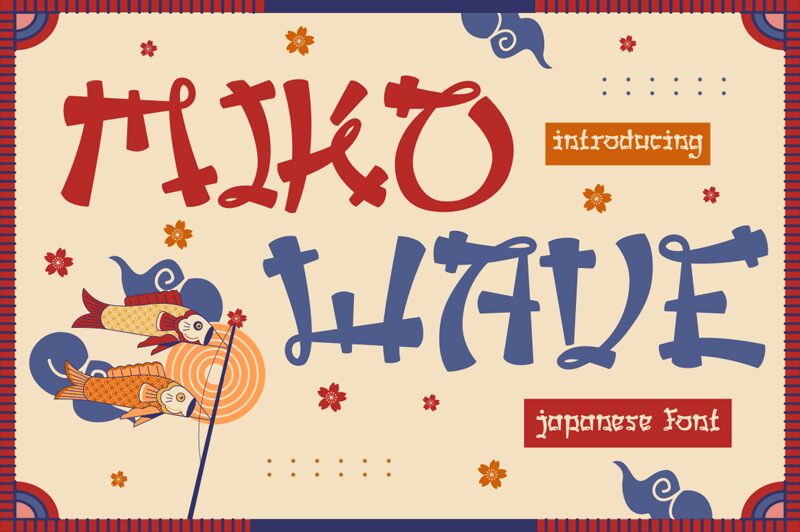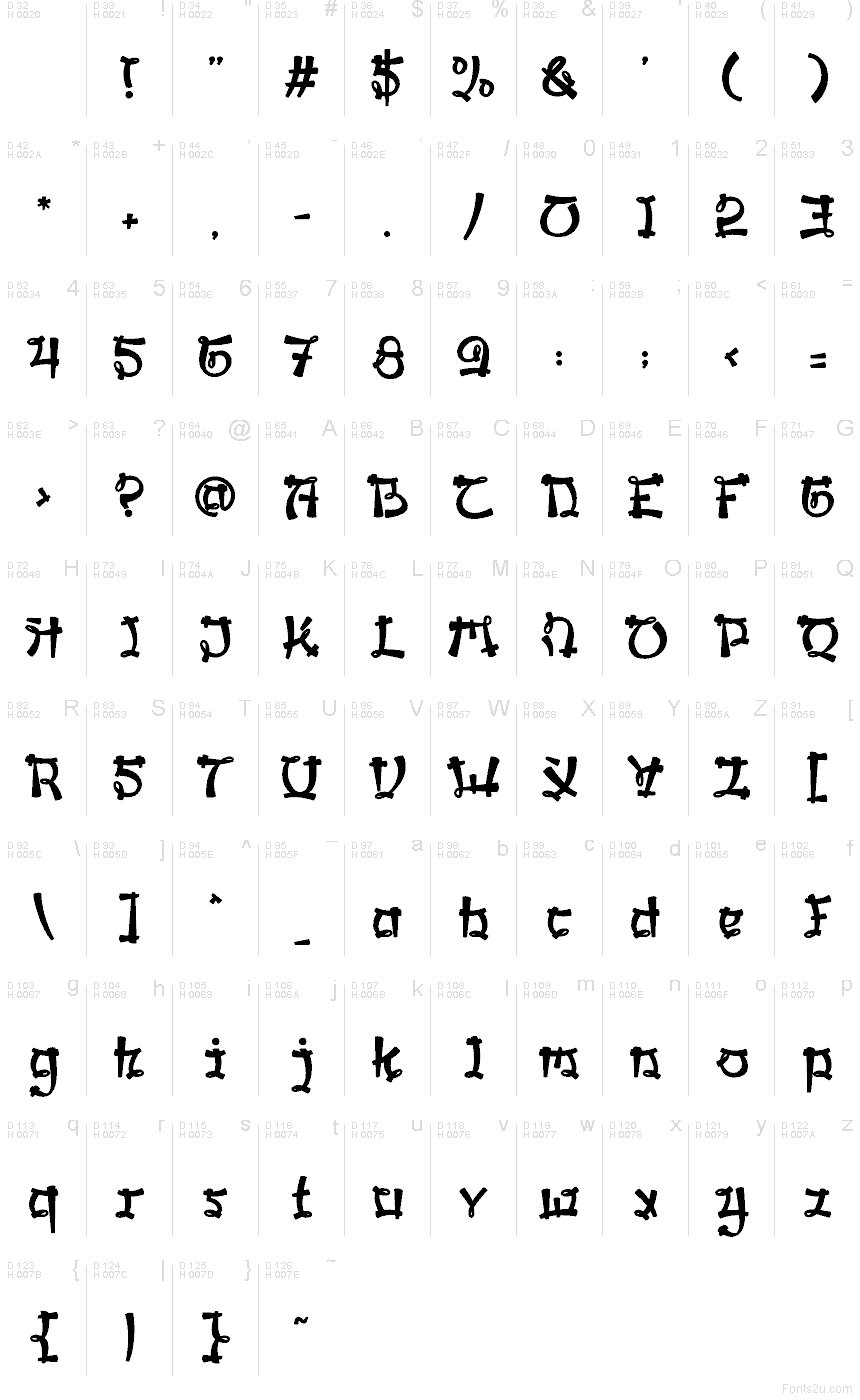
Miko Wave od Shanaf Studio je bezplatné písmo v japonském stylu štětce, které působí hravě a ručně malovaným dojmem. Písmena vypadají měkce, robustně a lehce nekonvenčně. Zaoblené tahy, tečky připomínající kapky a rozmáchlé háčky dodávají písmu rytmus, který je spíše zábavný než formální.
Díky tomu se přirozeně hodí pro branding kaváren, obaly pochutin, nadpisy na plakátech, titulní karty i krátkou grafiku pro sociální sítě – zkrátka všude tam, kde bezplatné písmo potřebuje vnést teplo namísto přísného řádu. Dobře funguje také u merchandisingu nebo rychlých návrhů log, protože štětcová váha a smyčkové detaily dodávají i krátkým slovům živý, rukou psaný náboj.
Miko Wave